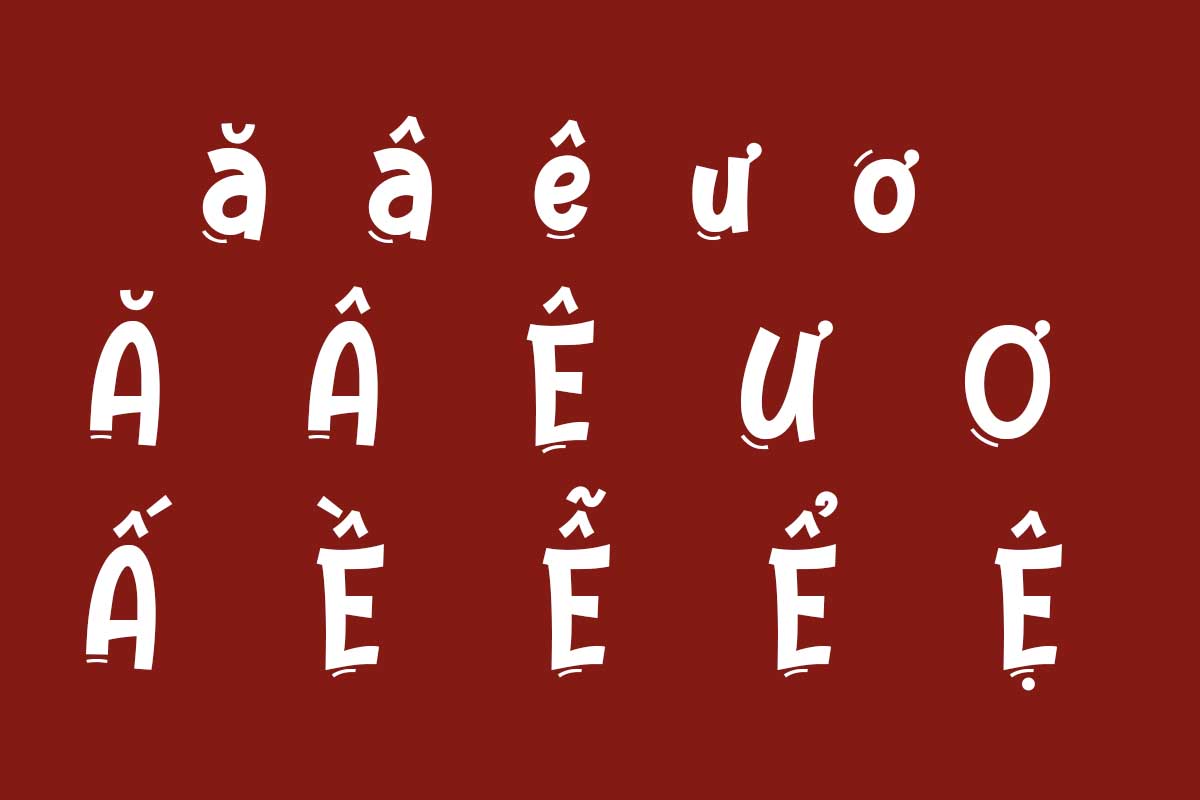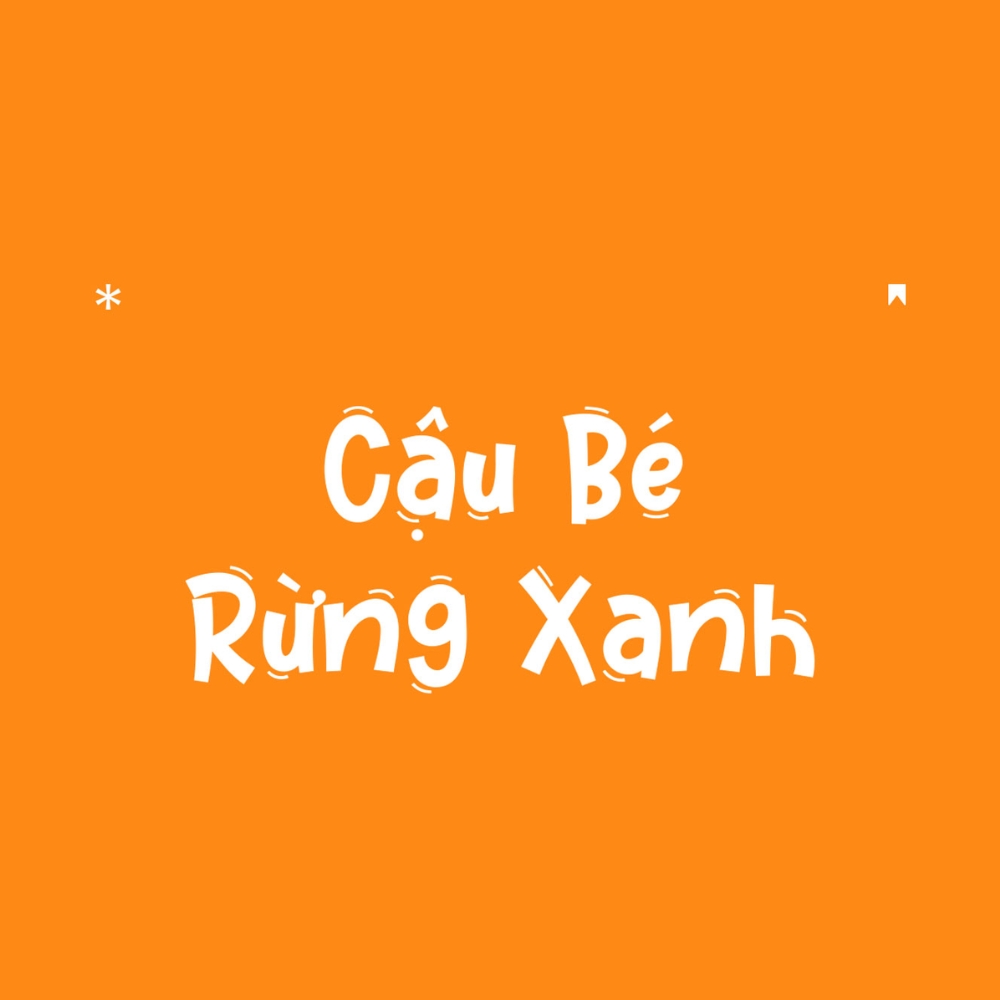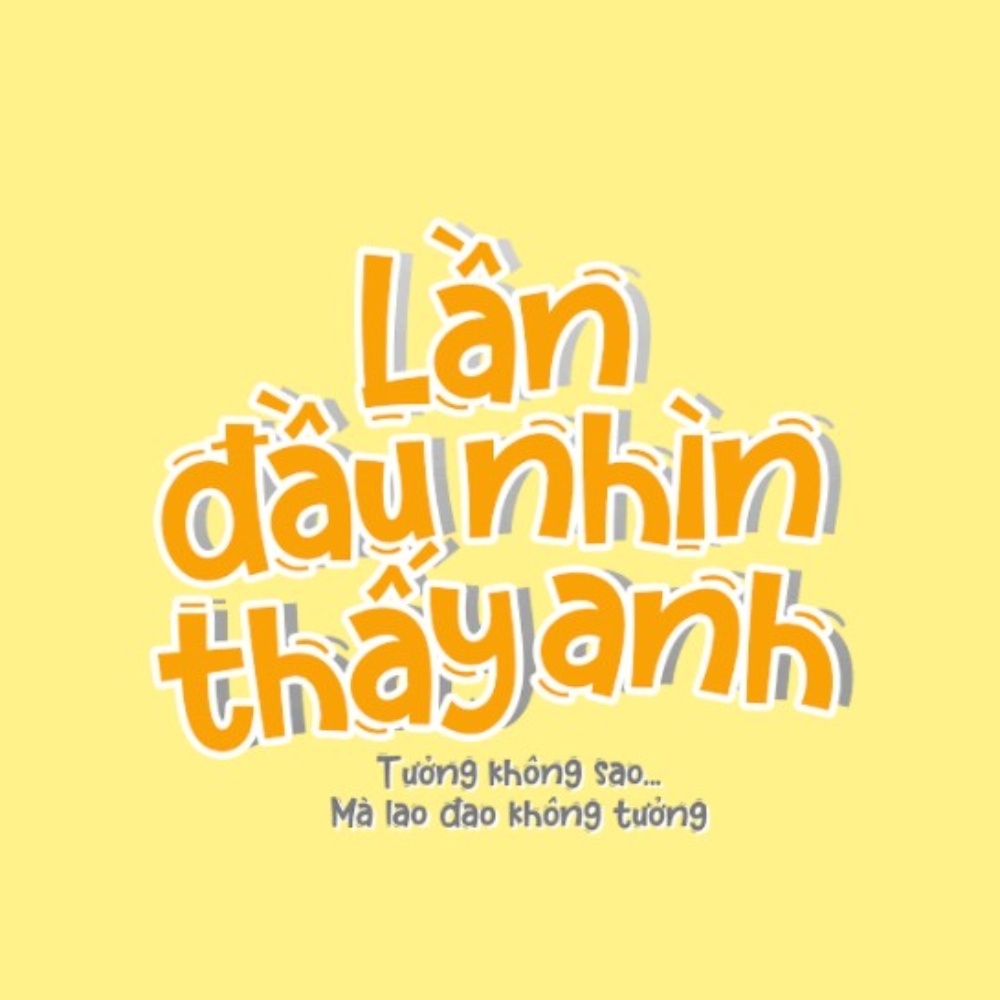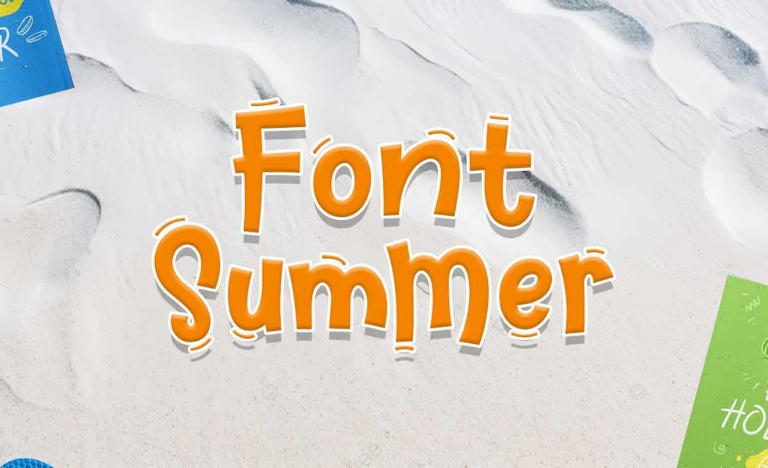
MTD Summer Show là bộ font chữ mang đậm hơi thở rực rỡ của những ngày nắng, với các đường nét ngẫu hứng và đầy sự tươi mới. Đây là một đại diện tiêu biểu của phong cách chữ viết tay vui nhộn, thường được lựa chọn để khơi gợi cảm hứng về sự tự do, năng động và thân thiện. Font Việt hóa MTD Summer Show ra đời nhằm giúp người làm sáng tạo tại Việt Nam có thêm công cụ trình bày ý tưởng mà không gặp phải các trở ngại về lỗi ký tự tiếng Việt.
Sức hút từ phong cách của font Việt hóa MTD Summer Show
Dòng font này sở hữu cấu trúc chữ không đồng nhất một cách có ý đồ, tạo nên nhịp điệu nhấp nhô đầy thú vị. Các nét chữ được bo tròn mềm mại, loại bỏ cảm giác khô cứng của những kiểu chữ in ấn truyền thống. Font chữ hoạt hình MTD Summer Show Việt hóa giúp các bản thiết kế trở nên sinh động và gần gũi hơn, đặc biệt phù hợp với những dự án hướng tới đối tượng trẻ em hoặc các không gian thư giãn nghỉ dưỡng.
Bên cạnh yếu tố thẩm mỹ, MTD Summer Show còn truyền tải năng lượng tích cực thông qua vẻ ngoài “mềm mại” và phóng khoáng. Khi sử dụng font mùa hè Việt hóa này, các thông điệp truyền thông thường mang lại cảm giác dễ chịu, vui tươi, giúp rút ngắn khoảng cách giữa thương hiệu và khách hàng. Đây là giải pháp hiệu quả cho những ai muốn tìm kiếm sự phá cách nhưng vẫn giữ được tính ứng dụng cao trong các hồ sơ thiết kế và ấn phẩm đồ họa.
| Phân loại phong cách | Handwritten / Cartoon / Summer style |
| Đặc tính hiển thị | Bo tròn, nhịp điệu tự do |
| Mục đích phù hợp | Tiêu đề, Poster, Bảng tên phòng, Menu |
Gợi ý phối hợp: Do summer font Việt hóa có tính trang trí rất mạnh, bạn nên kết hợp nó cùng một font không chân (Sans-serif) đơn giản cho phần nội dung chi tiết. Sự tương phản giữa nét chữ hoạt hình vui nhộn và sự gọn gàng của văn bản phụ sẽ tạo nên một bố cục chuyên nghiệp và dễ tiếp nhận thông tin.
03 Ứng dụng font chữ hoạt hình MTD Summer Show Việt hóa
Nhờ vẻ ngoài giàu tính thẩm mỹ và tràn đầy năng lượng, bộ font chữ này mang lại giá trị thực tế cao khi được đưa vào thực tế trang trí và quảng bá công trình:
- Bảng tên cho Homestay và Cafe ven biển: Những nét chữ tròn trịa của font mùa hè Việt hóa rất ăn ý khi xuất hiện trên các biển hiệu gỗ hoặc alu màu sắc rực rỡ. Đối với các dự án nhà lắp ghép nghỉ dưỡng, font chữ này giúp không gian trở nên trẻ trung và thu hút khách du lịch.
- Trang trí khu vui chơi và phòng trẻ em: Bạn có thể dùng font MTD Summer Show để thiết kế các bảng tên phòng, decal dán tường tại các khu vực dành cho trẻ nhỏ trong các căn hộ hiện đại. Nét chữ đầy đặn tạo cảm giác vui tươi và an toàn.
- Ấn phẩm quảng bá sự kiện mùa hè: Sử dụng font này cho các tiêu đề chính trên banner hoặc poster sẽ giúp thông tin trở nên nổi bật, dễ dàng tạo ra sự kết nối về mặt cảm xúc với khách hàng ngay từ cái nhìn đầu tiên.
03 Lưu ý kỹ thuật khi sử dụng summer font Việt hóa trong thiết kế
Để khai thác tối đa vẻ đẹp của dòng font chữ vui nhộn này mà không làm ảnh hưởng đến thẩm mỹ chung, người thiết kế nên lưu tâm một số điểm sau:
- Kiểm soát khoảng cách dòng: Do cấu trúc chữ có nhịp điệu nhấp nhô, các dấu thanh tiếng Việt có thể vươn cao. Bạn nên nới rộng khoảng cách dòng để các ký tự không bị chồng chéo, giữ được sự thông thoáng cho văn bản.
- Ưu tiên làm tiêu đề điểm nhấn: Tránh sử dụng font hoạt hình cho các đoạn văn bản hướng dẫn dài hay hồ sơ kỹ thuật. Hãy để nó tỏa sáng ở vị trí tiêu đề, slogan hoặc các cụm từ ngắn cần sự chú ý mạnh mẽ.
- Lựa chọn màu sắc rực rỡ: MTD Summer Show phát huy hiệu quả thị giác cao khi phối cùng các tông màu nóng hoặc màu pastel sáng, giúp tôn vinh tinh thần mùa hè và sự năng động của bộ chữ.